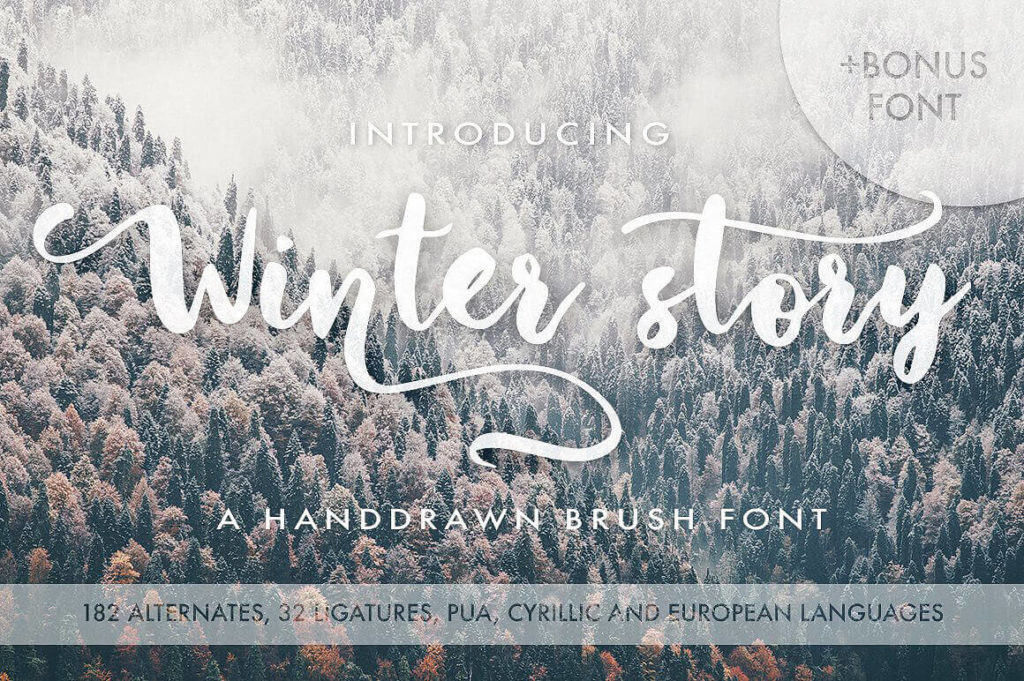
Шрифт Winter Story
декоративный рукописный скрипт от дизайнера Yur Lis и студии Stripes Studio. Имитируя естественное написание кистью или пером, он обладает характерным «прыгающим» ритмом и плавными связками букв. Мультиязычная кириллица и латиница делают его универсальным инструментом для создания выразительных заголовков. Элегантный и праздничный характер начертания идеально подходит для свадебной полиграфии, зимних коллекций и авторской айдентики. Скачать бесплатно можно для личных проектов, однако перед коммерческим использованием лицензию необходимо уточнить у правообладателя.